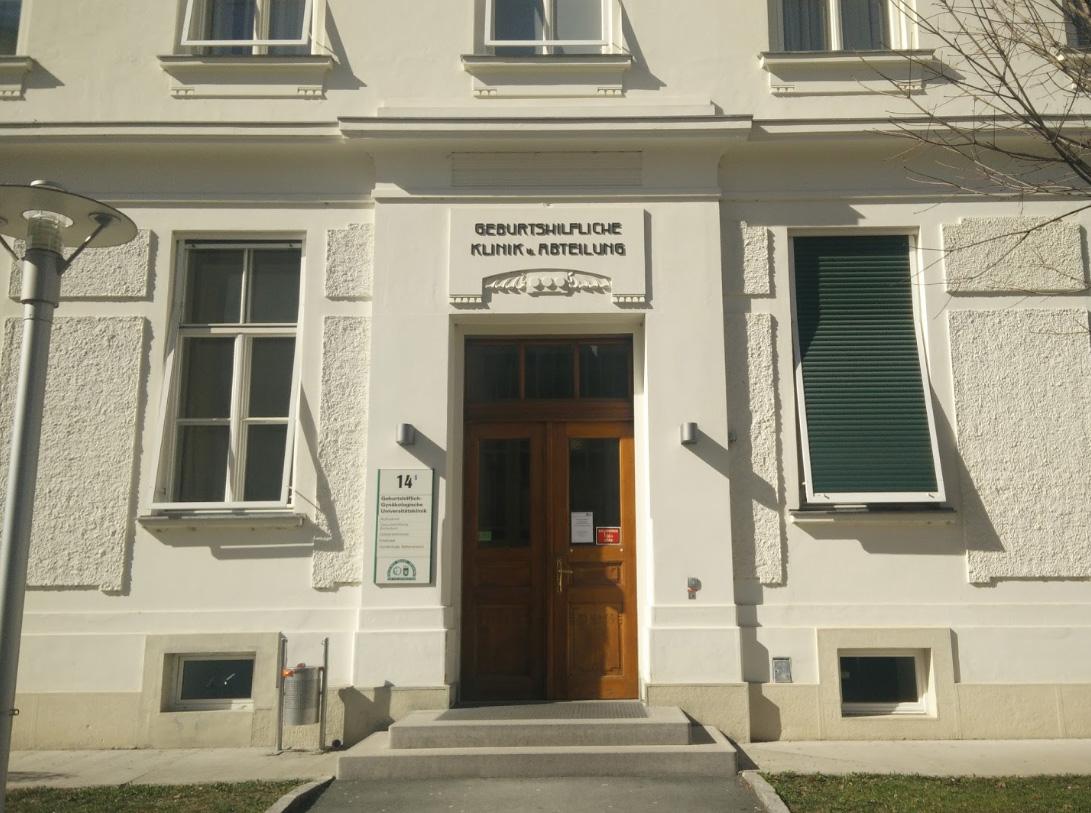
Jugendstil- oder Secessions-Schrift
Gibt es von dieser Schrift, welche am Eingang eines Hauses im Jugendstil angebracht ist eine digitale Version?
Oder zumindest eine Ähnliche??
Höchst wahrscheinlich nein. Also ein gutes Bild, nur von der Schrift machen, dann kann man die als Schrift sicher leicht erstellen.
Gerade Hausanschriften wurden damals eigentlich immer frei gestaltet, und daher gibt es eben eine recht große Auswahl derartiger Schriften die oft eben nur aus einer Hand voll Buchstaben bestehen, und die nie digitalisiert wurden. Hier wurden ja vorrangig Satzschriften in die neue Technik übertragen.
Leider hab ich kein besseres Bild - und das Gebäude ist 600 km entfernt :-) (also mal schnell ein Bild machen klappt leider nicht). Ich hab ohnehin vermutet, dass ich hier keine Font finden werde. Dann werden wir uns halt als "nachbasteln" wagen...